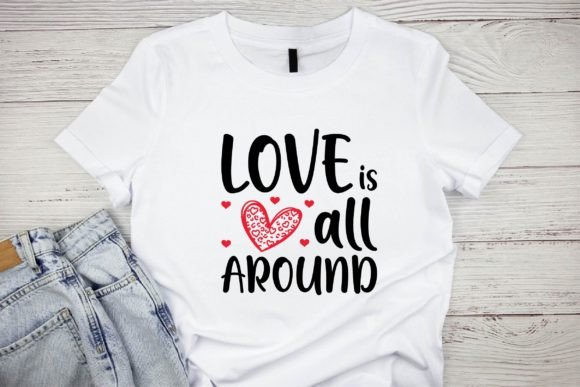
Love is All Around
Если вы ищете высококачественные ресурсы, такие как Love is All Around, этот премиум-пакет — фантастический выбор для ваших творческих проектов.
Создаете ли вы продукты POD (печать по требованию), свадебные приглашения или графику для социальных сетей, Love is All Around станет идеальным выбором.